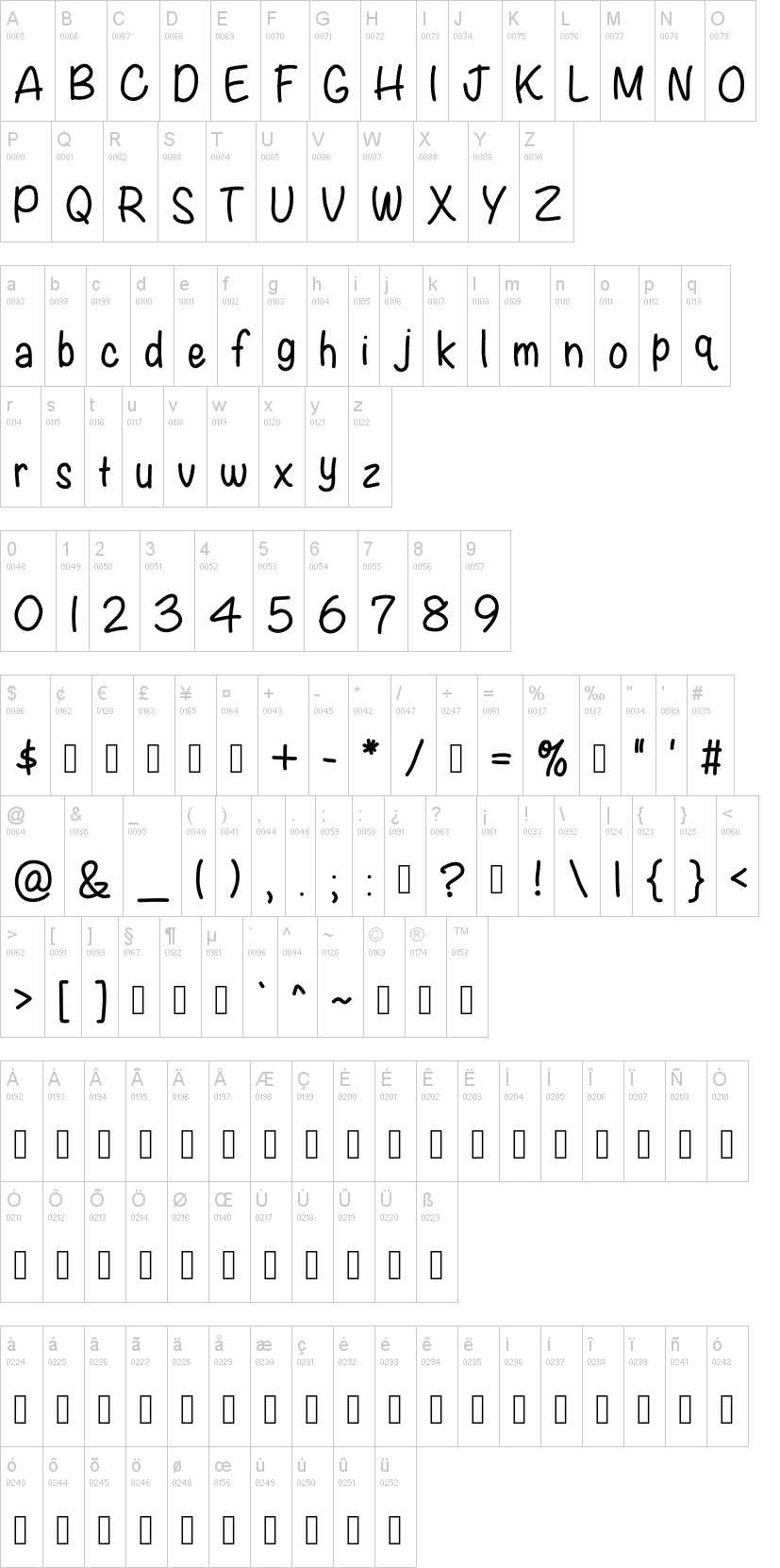
? KB Writers Block 是一款简洁、抒情的字体,由著名设计师 Kady Babs 创作。它的特点是非常细腻,具有柔和的曲线,体现出一种柔和的抒情感。它的字体比较宽,比较大,而且有着比较明显的特点,使得字体看起来更加明显,更加突出。KB Writers Block 字体具有简洁、优雅的风格,适合用于文字、标题、标签等等。内容介绍
KB Writers Block是一款非常不错的手写艺术字体,具有很好的视觉感,适合于文化类的宣传设计、商业类品牌的广告和产品包装设计以及个性化文字排版等较多场景。